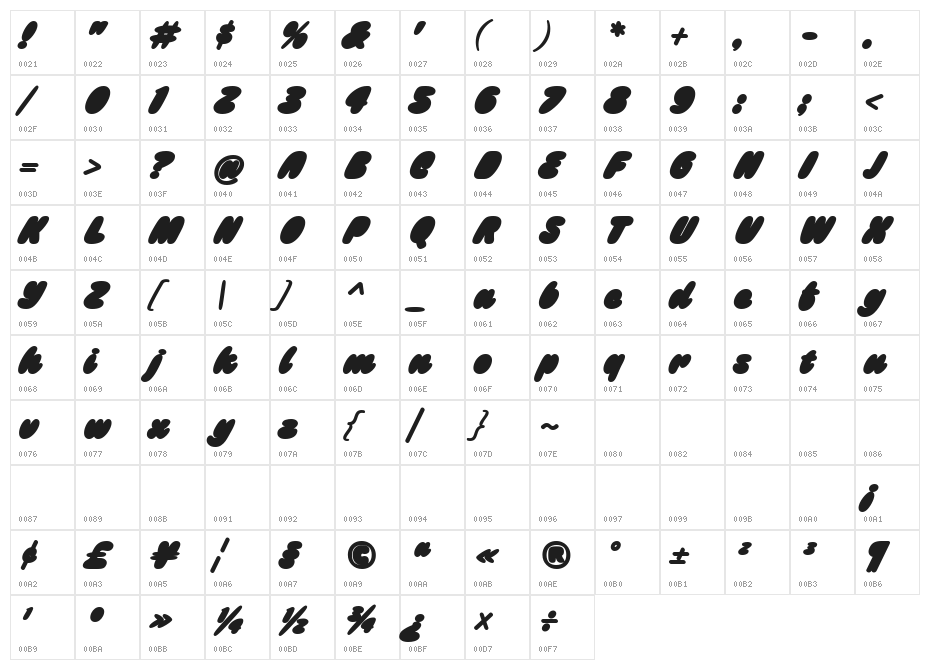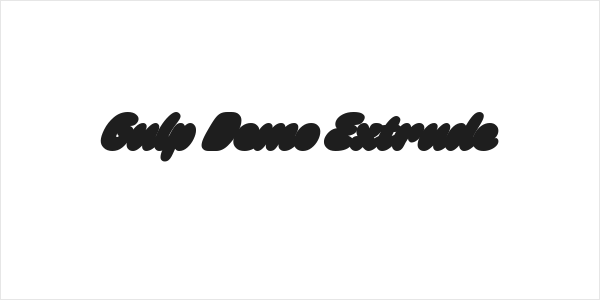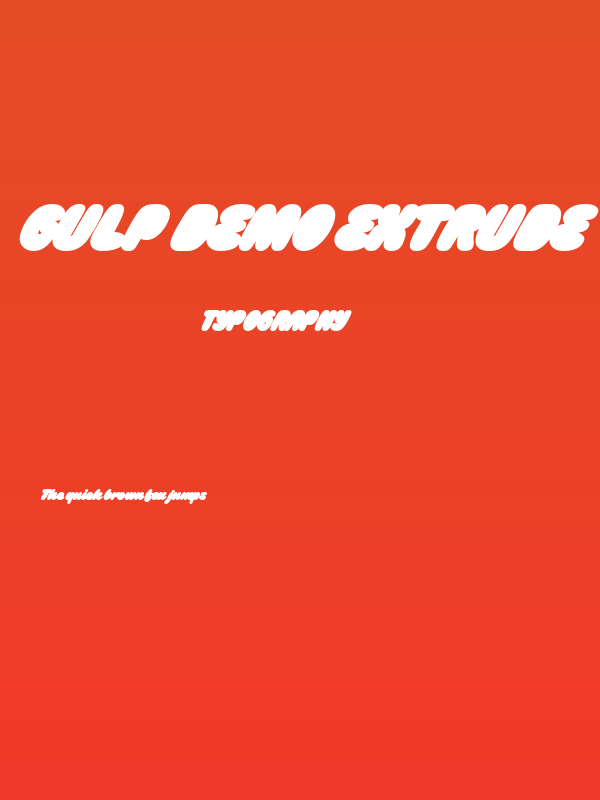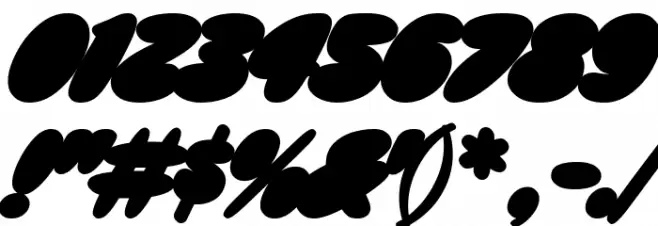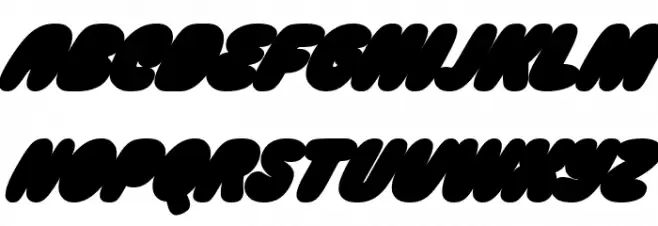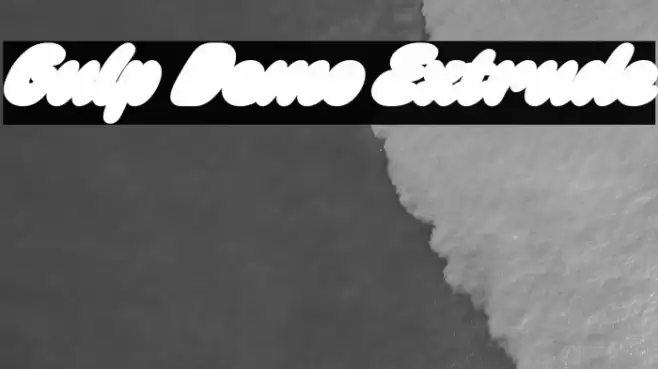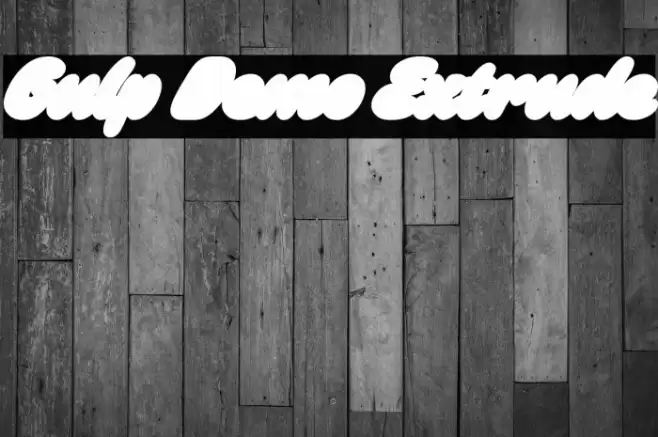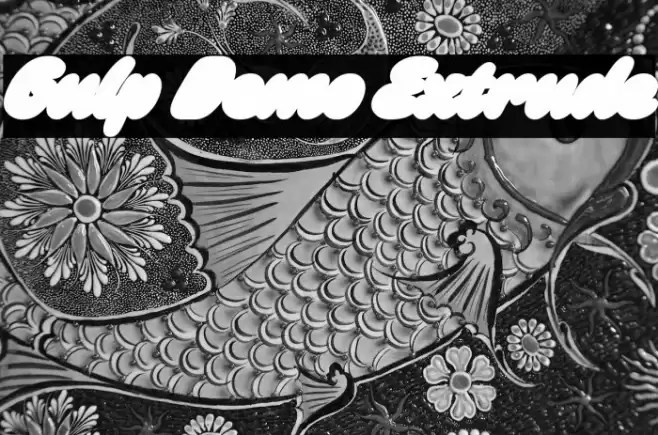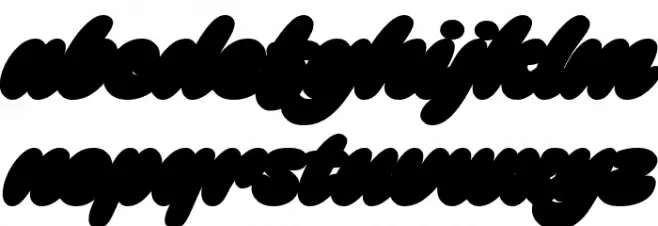
Gulp Demo Extrude Font
| Ancho | Expanded |
| Estilo general | Retro, Playful |
| Proyectos propuestos | Ideal for posters, children's books, playful branding, and retro-themed designs. |